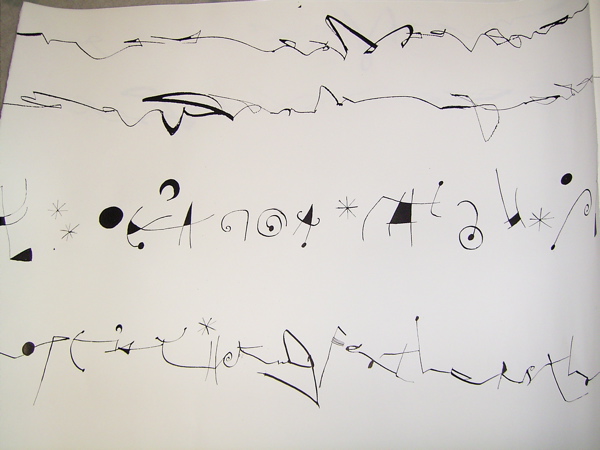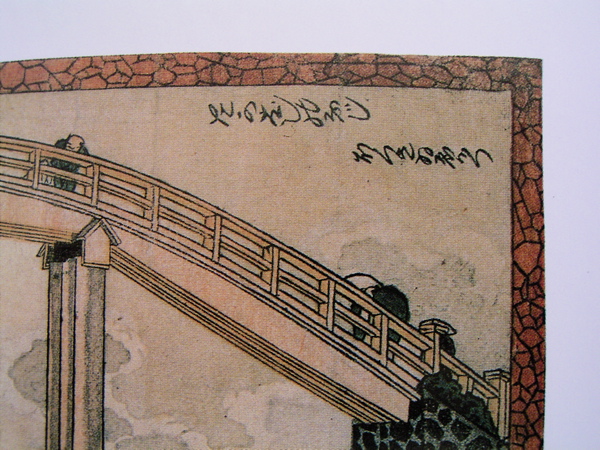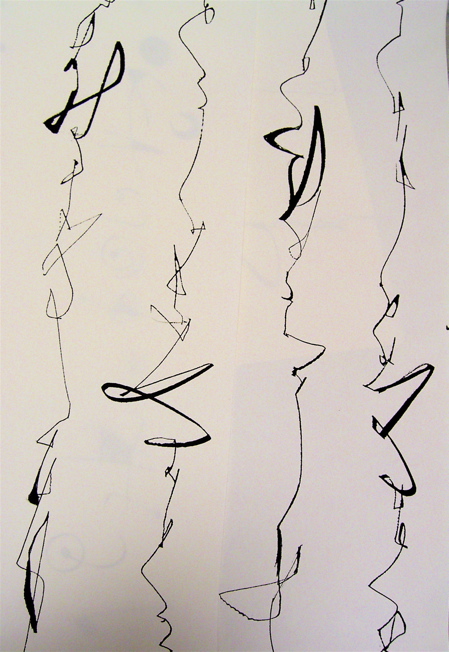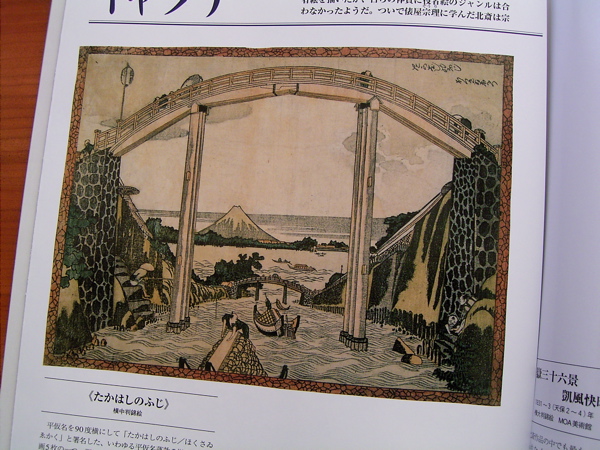
北斎のひらがながき
その、たかはしのふじの右上を見て、驚き!!なんと、アルファベット風に見せるために、縦書きの名前(落款)を横にして書いているのです。「たかはしのふじ」というひらがなと、「ほくさいゑがく」と書いてあります。
これを見てとっても感動!北斎がアルファベット風にしようとしたところも非常に面白いのですが、実はもう一つ理由があります。
それは、昨年受講したBrody Neuenschwandar氏のワークショップでやった内容と同じだったからです!そのワークショップでは、まずアルファベットを縦書きに一筆で書きます。それからそれを横にしてみます。その形から発想を得て文字にしていくという進め方でした。
2ヶ月経ったので何の文章を書いたかは忘れてしまいましたが、コーラペンで右から縦に書きました。ところどころ、サイズとウェイトを変えてコントラストをつけています。
最終的にはここまで行きつきました。上の2行は縦書きを横にしたもの。次の2行は、ご存知ミロの文字の様なシンボル。そしてこの二つを合体させたもの(させようと努力したもの)が最後の1行。
たしか時間がなくて、あまり追求出来ずに書いたので、今見るとあまりうまく合体していないですよねー。
Brodyはプリンストン大学を卒業後イギリスで美術史の博士号を持っているので、もしかしたら北斎の「ひらがながき」を知っていたのかもしれません。
それにしてもカリグラフィーのワークショップで北斎とつながっていたことをやっていたなんて!
奥が深いな〜〜〜〜。